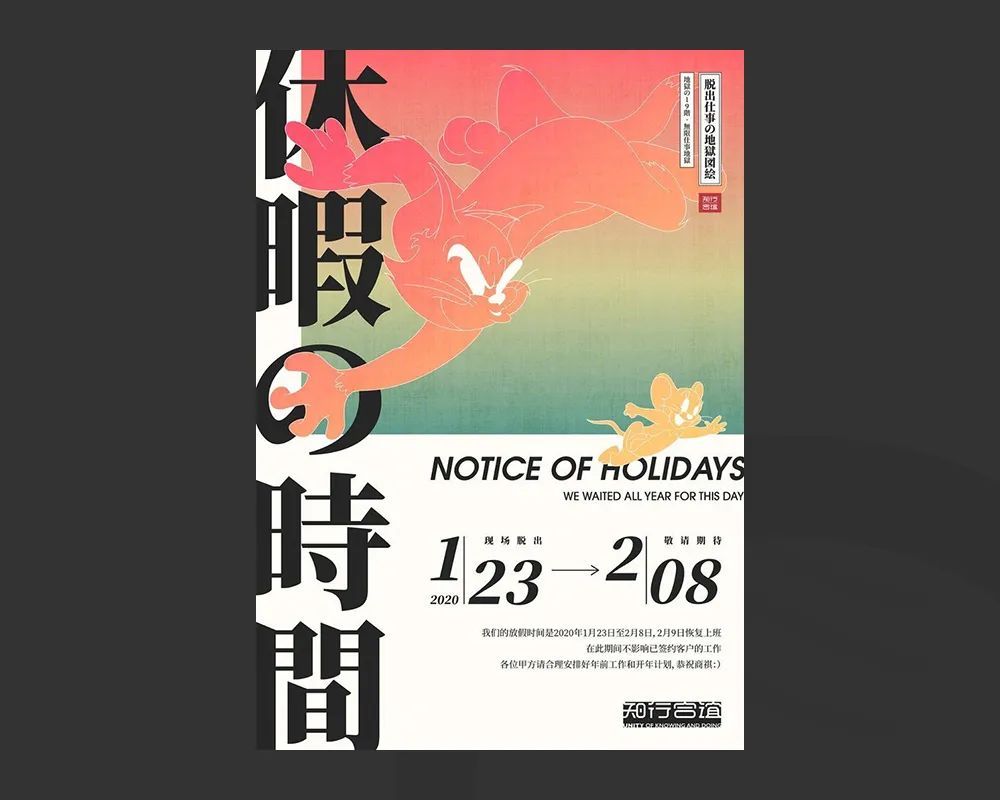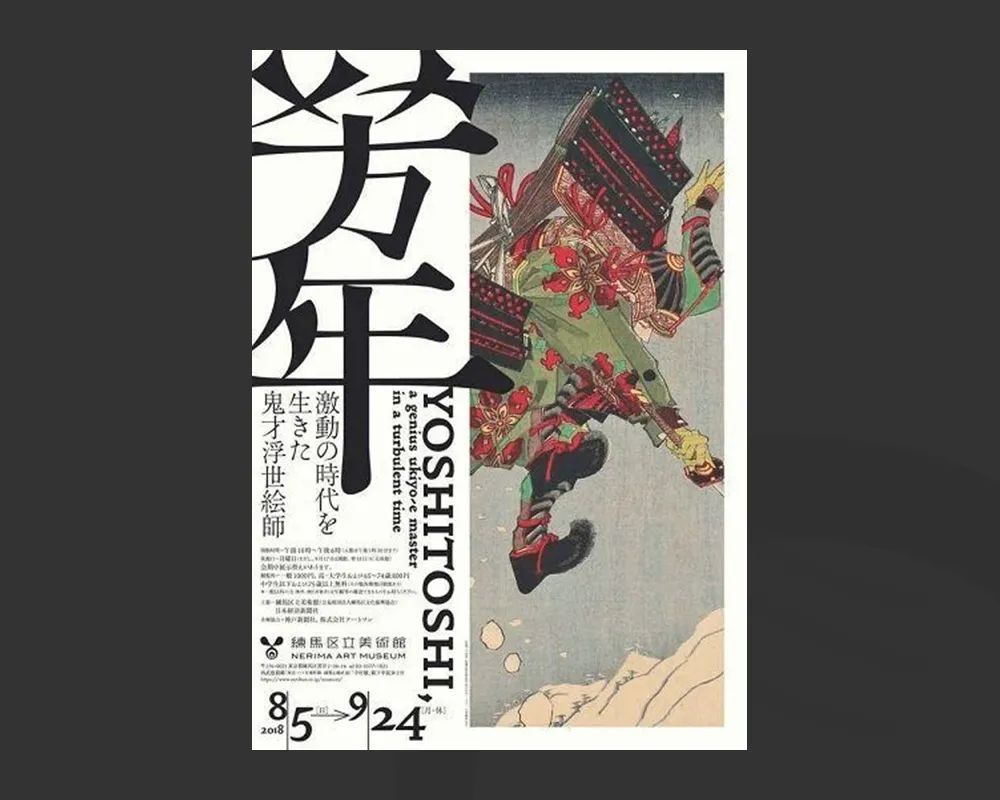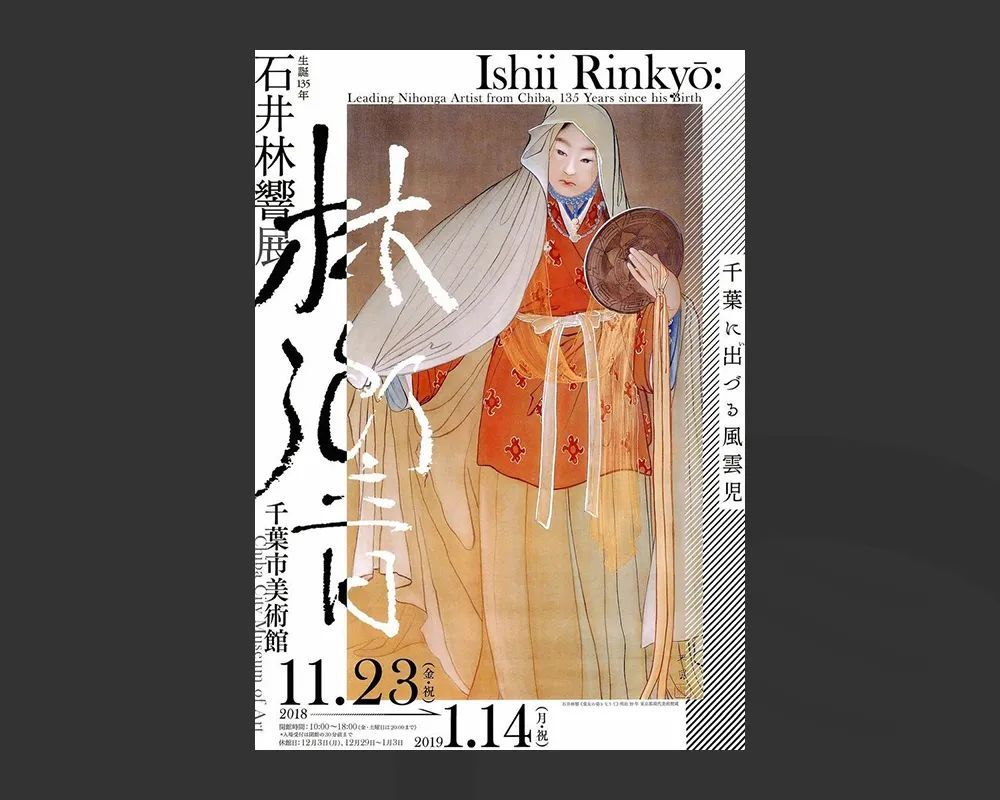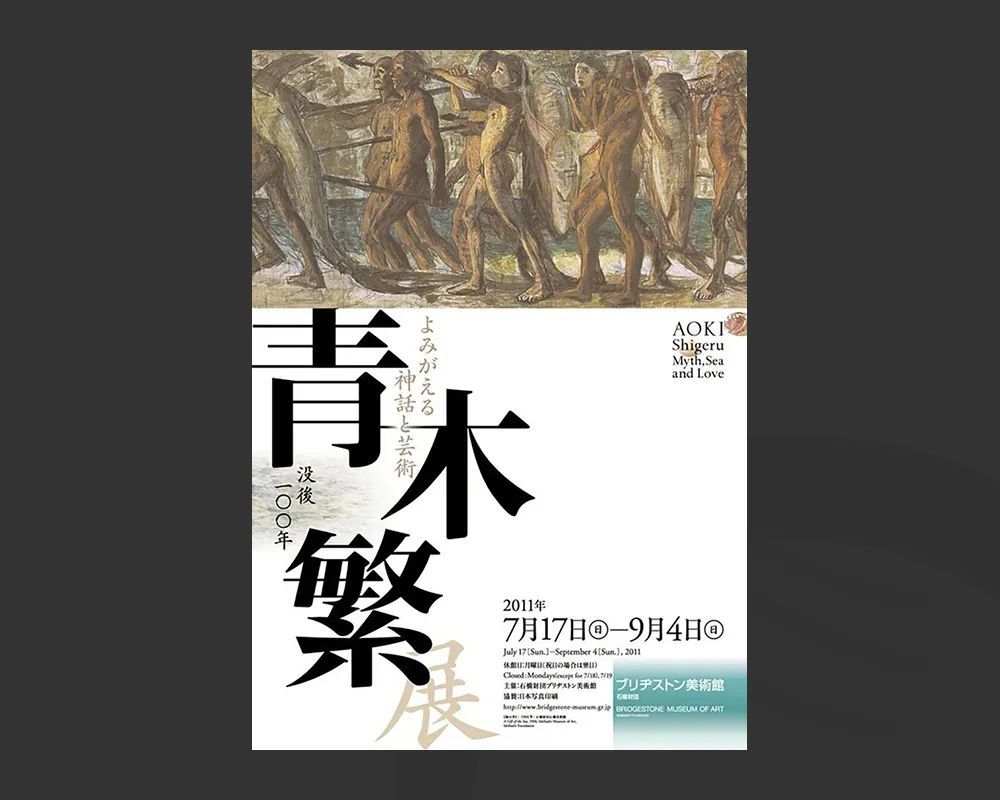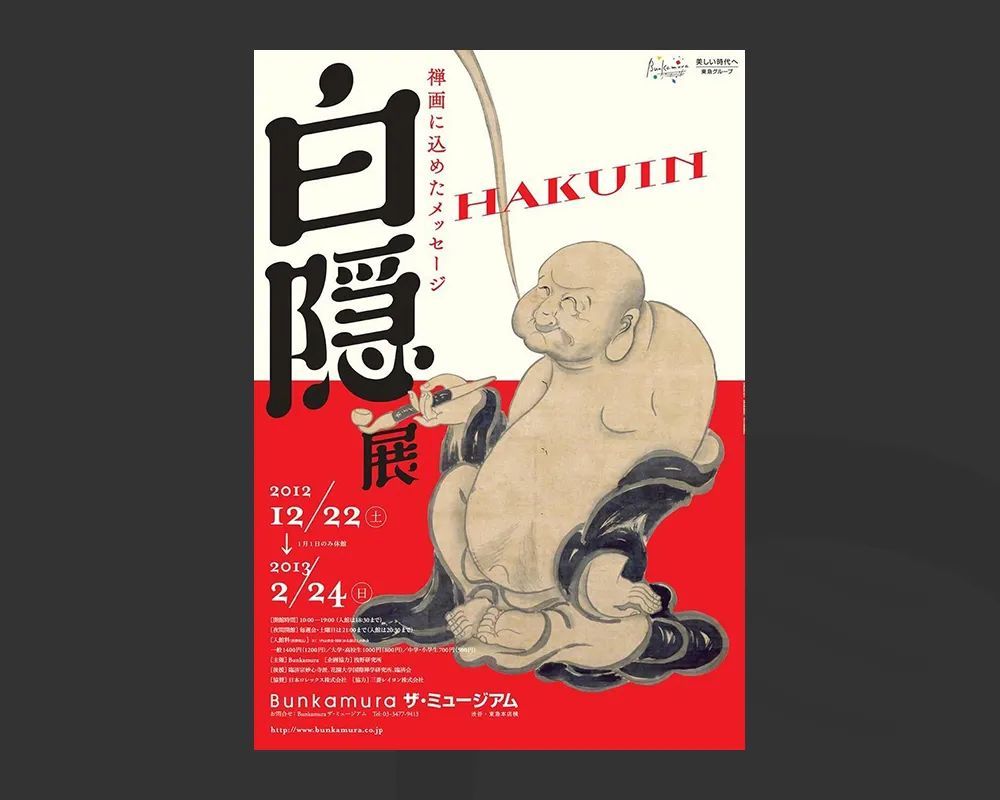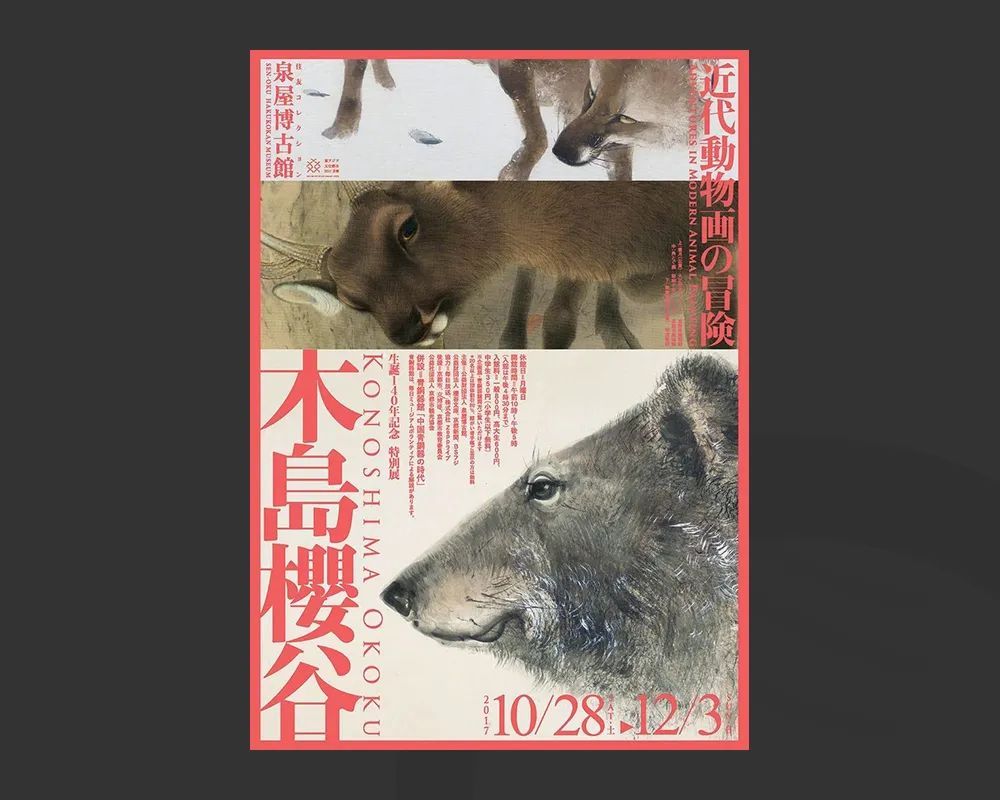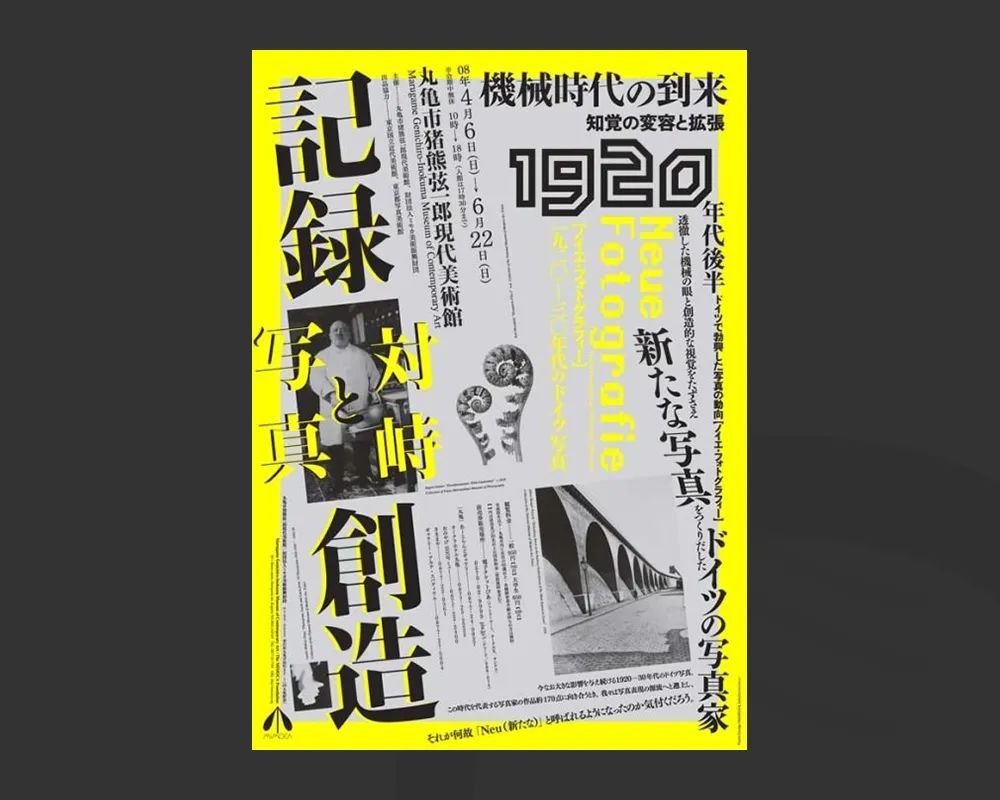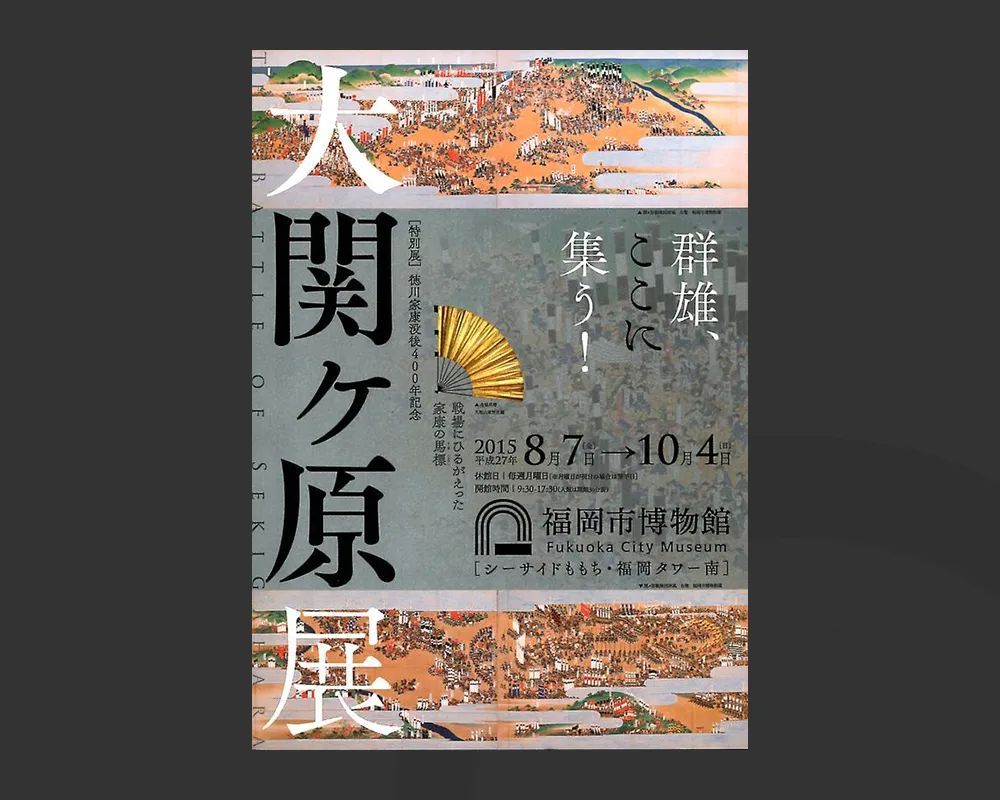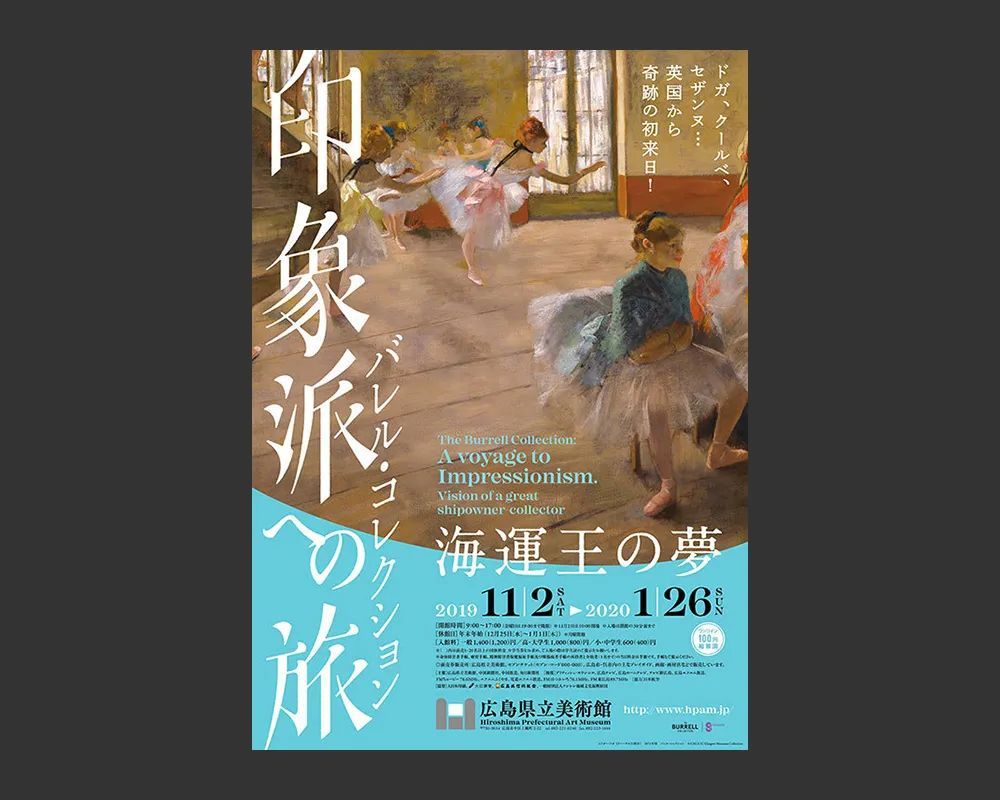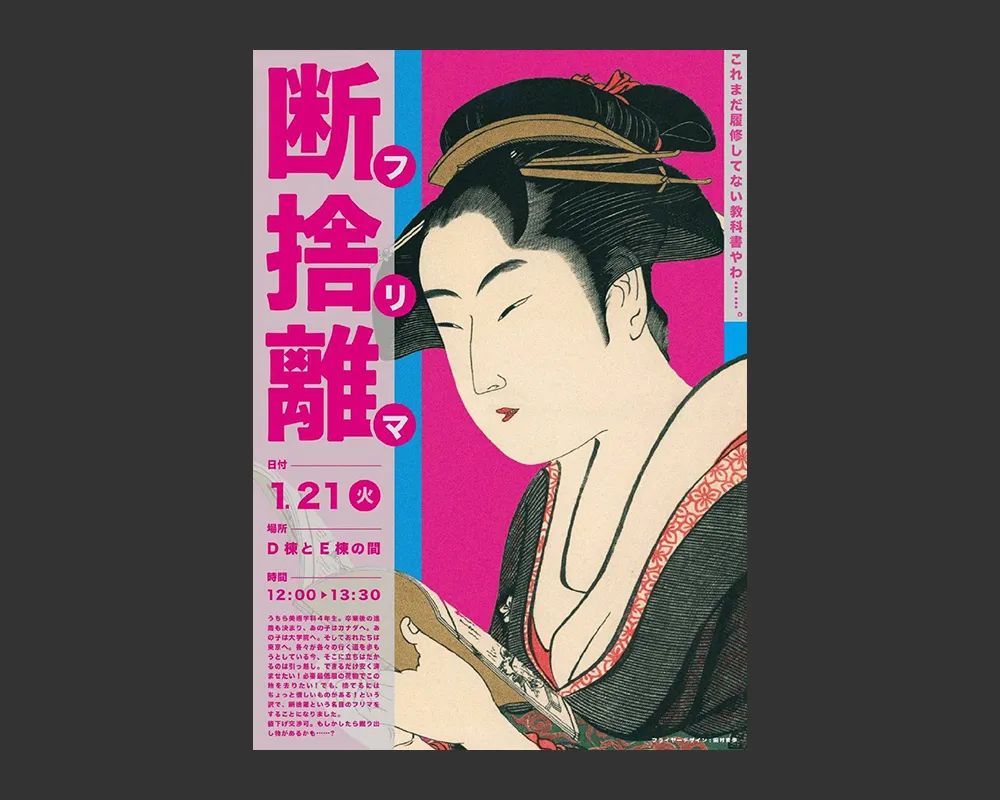
标题字体:咱个头大,靠左边站
在日常的设计工作中,字体的选择和文字排版,对于整体设计的表达起着至关重要的作用。如何划分层次、突出重点、充分结合整体风格、将文字编排工作做得富有趣味性、设计感、吸引眼球、准确的传达信息等等,都是十分考究设计师能力的。
我们都知道,文字排版有三大原则:对齐、对比、分组。就拿对齐来说,常见的文字排版有左对齐、右对齐、居中对齐、上对齐、下对齐、两端对齐等等。今天主要和大家聊聊看看「标题字:左对齐,字够大」。
为了方便大家更直观理解,我整理了一些海报设计作品。作品中的标题字主要使用了“左对齐”靠边站的的排版形式,这些作品有个共同点就是搭配大大的字体标题。虽然画面中内容众多,但其主题文字突出,处理方式巧妙,整体非常和谐。
先看看一组日系海报:
从上面的海报当中,我们可以看到主要是使用宋体和黑体为主,有开心的、独特的、温柔的和深刻的。设计师只要稍微加上一些元素或图像进行组合,便能给人视觉上的刺激。再加上左对齐,非常有序。
日本设计师高桥善丸先生曾说过:“文字造型的关键是平衡,有时打破一些平衡,文字反而可以换一种表情。”
看看两张使用英文排版的海报:
文字左对齐,可以说是属于百搭的形式。字体的选择包括字号大小,要结合画面的构图形式、视觉重心,也就是将文字排版与构图形式合理的结合,两者相辅相成、互相作用。
下面是国内的中文海报作品:
对齐的目的,其实就是在规整文案信息,对齐有利于信息传达以及视觉规范。
这些优美的标题字体不仅造型漂亮,阅读时也不会给人增加负担。再加上足够大的标题字,可以说是极具吸人眼球!
海报设计的文字排版有很多处理方式,假如你不知道标题字体该如何处理,不妨试试将标题字体左对齐,然后放大再放大,通过强烈的大小对比来加强画面的张力。